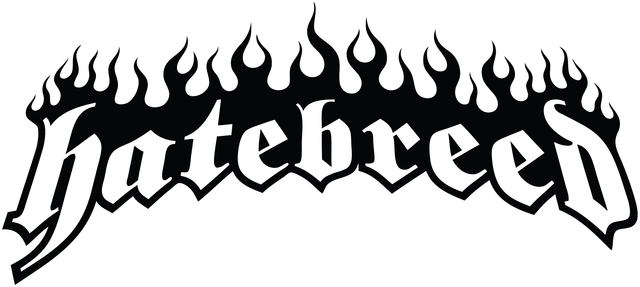
Schrift von Tattoo
Hatebreed als Vertreter von Metalcore?, Heavy Metal?, Punkmetal? verdient latürnich eine kaputte Gebrochene. Jedenfalls irgendwas der Kategorie distressed. Oder als Kontrastprogramm die angepassteste: Helvetica.
ok, fein... wir kommen zurück zur typografie.
das hatebreed logo besteht ja aus einer fetten fraktur, dazunoch verzerrt, find ich hier eigentlich ganz passend.
mal abgesehen davon das handgemacht immer individueller ist ...
ich finde die schrift vom tattoo gar nicht so verkehrt, hätte man den zeilenabstand etwas angepasst und die buchstaben nicht 1:1 übernommen. nichts sieht blöder aus, als sich wiederholende formen in einer 'handschrift'. evtl. hätte man auch sowas
für das zitat verwenden können. das ganze mit etwas rot schattiert sieht bestimmt 'scharf' aus. ;-)
Na ja, der Gesang ist etwa so unverständlich wie die Schrift unlesbar ist. Welche Schrift sollte den nach Deiner Meinung besser passen?
Gute Frage, die ich mir bis dato auch noch nicht gestellt habe.
Da die Musik von Hatebreed sowohl bei der Instrumentierung als auch beim Gesang auf sämtliche Ausschmückung (die Grenze zum Banalen ist mitunter fließend) verzichtet, finde ich die Schriftvorschläge fast ausnahmslos unpassend. Wieso muss ein »unverständlicher Gesang« (der es meines Erachtens gar nicht ist) durch eine unleserliche oder gebrochene Schrift dargestellt werden? Das ist allenfalls ein ganz tiefer Griff in die Klischee-Kiste. :hammer:
Als passender empfinde ich amerikanische Groteskschriften, wie die Franklin Gothic, Trade Gothic oder Gotham.
okay, da bin ich bei dir. allerdings wird die kundin im besten fall zum tätowierer sagen:
"mach mir 'ne schreibschrift die zu meinem bauch, femininen charakter und zu den lyrics der band passt"
da ist eine amerikanische grotesk doch eher etwas für den behaarten rücken des bandleaders.